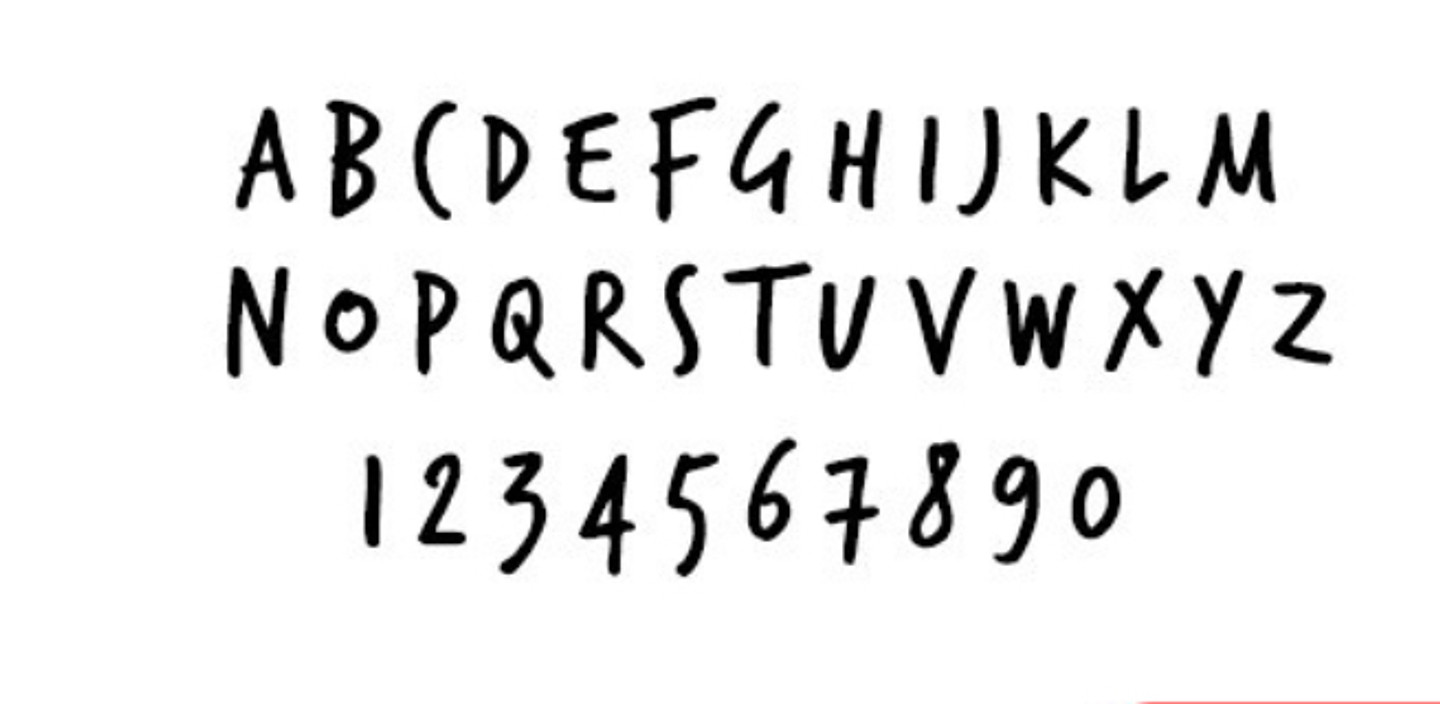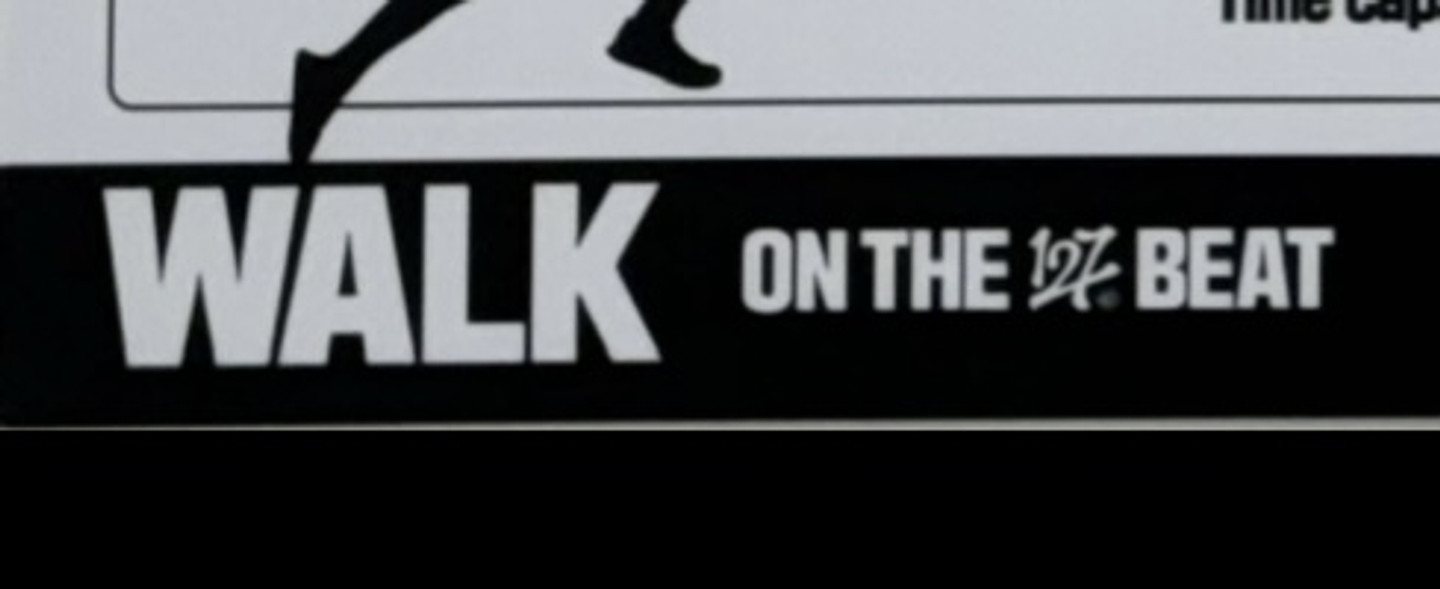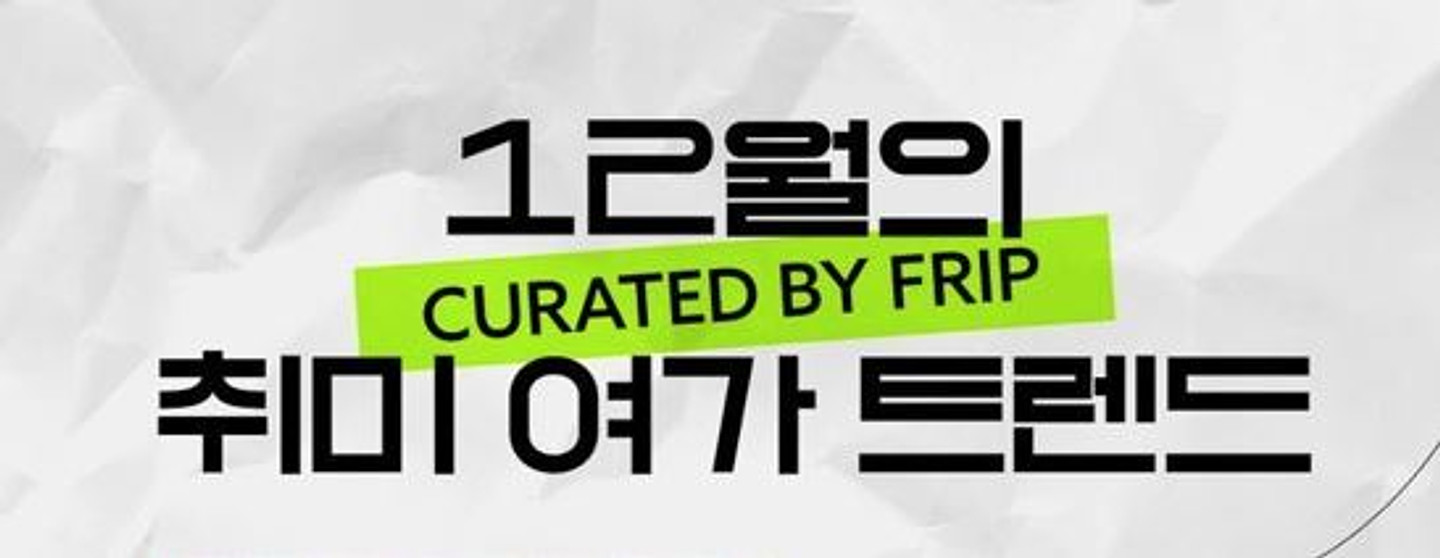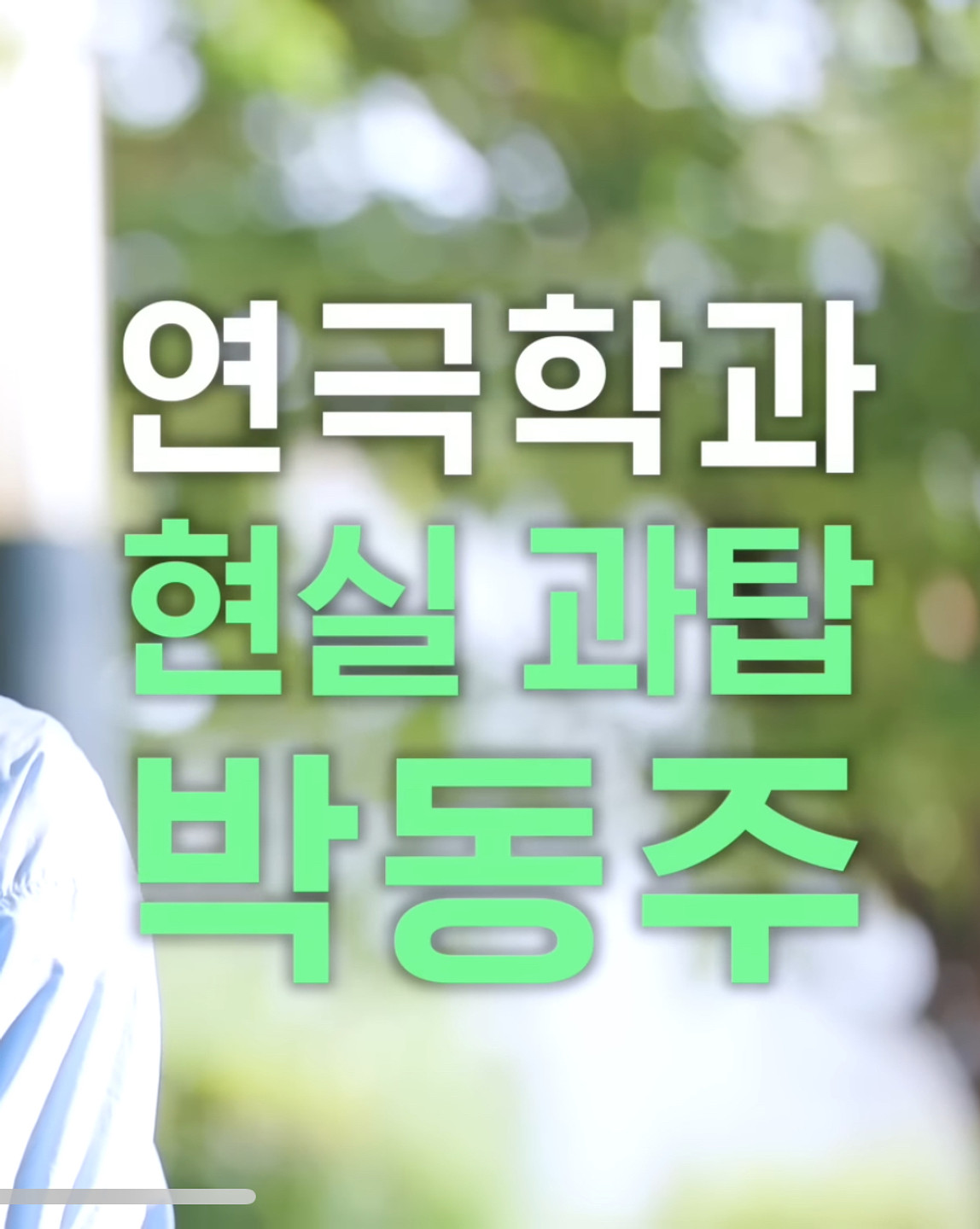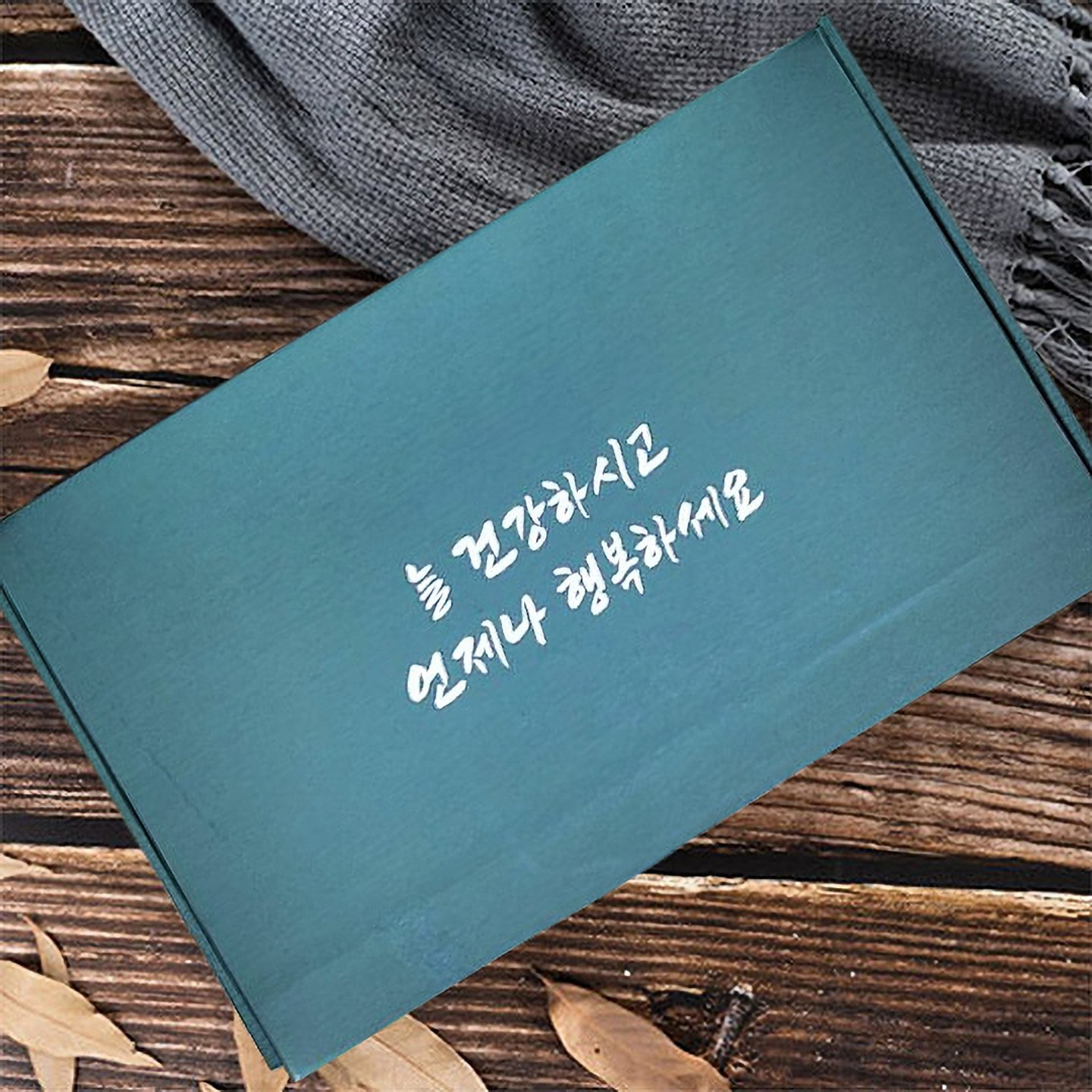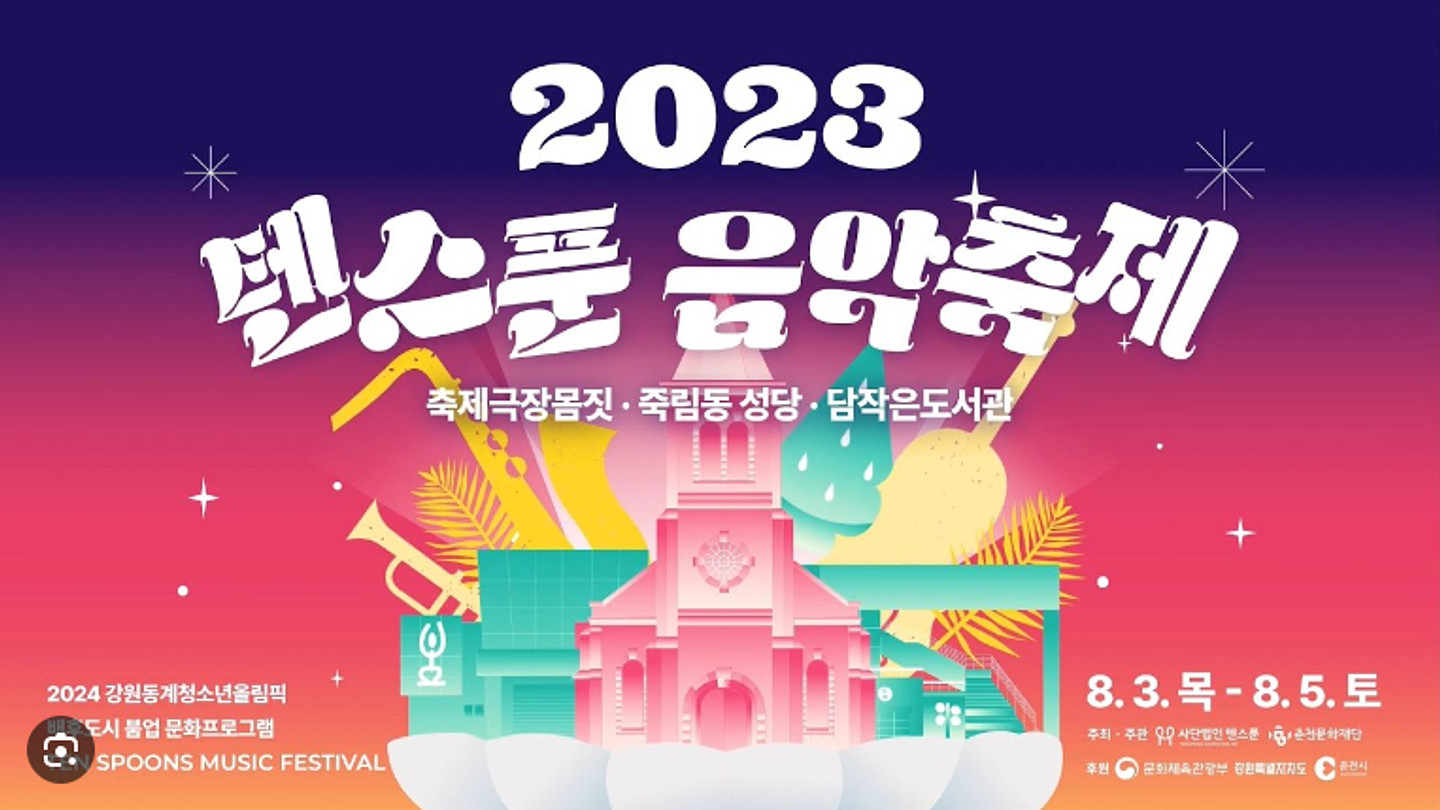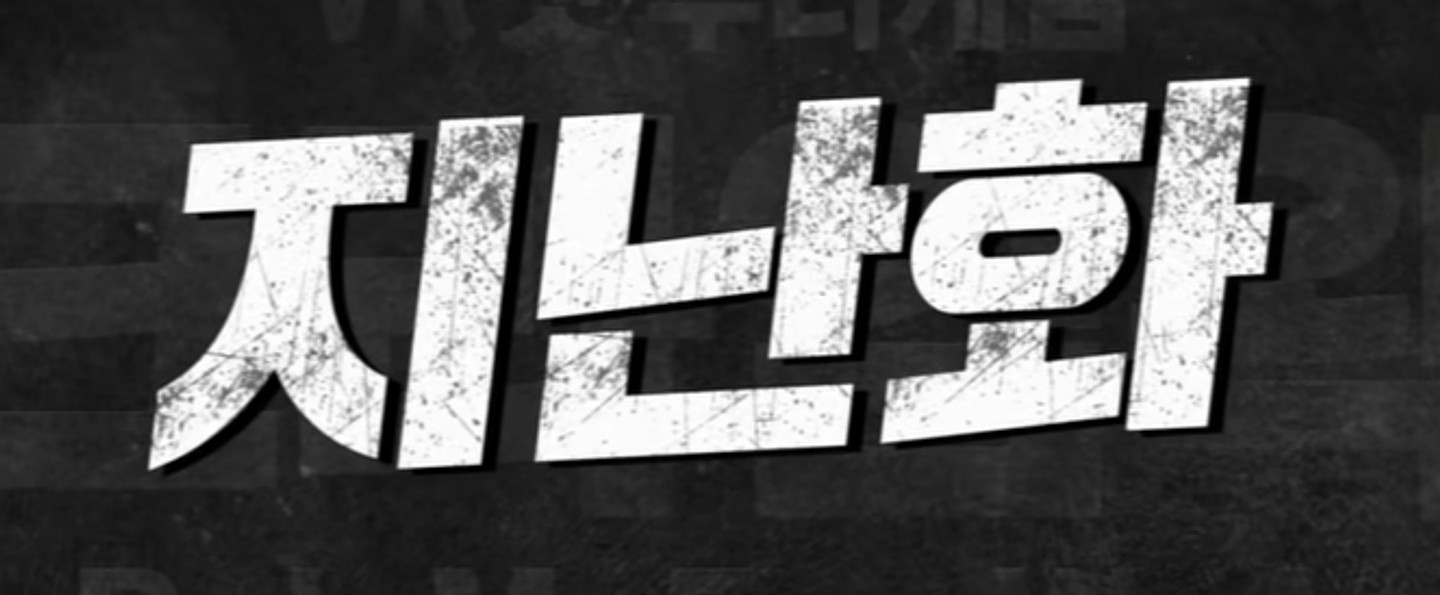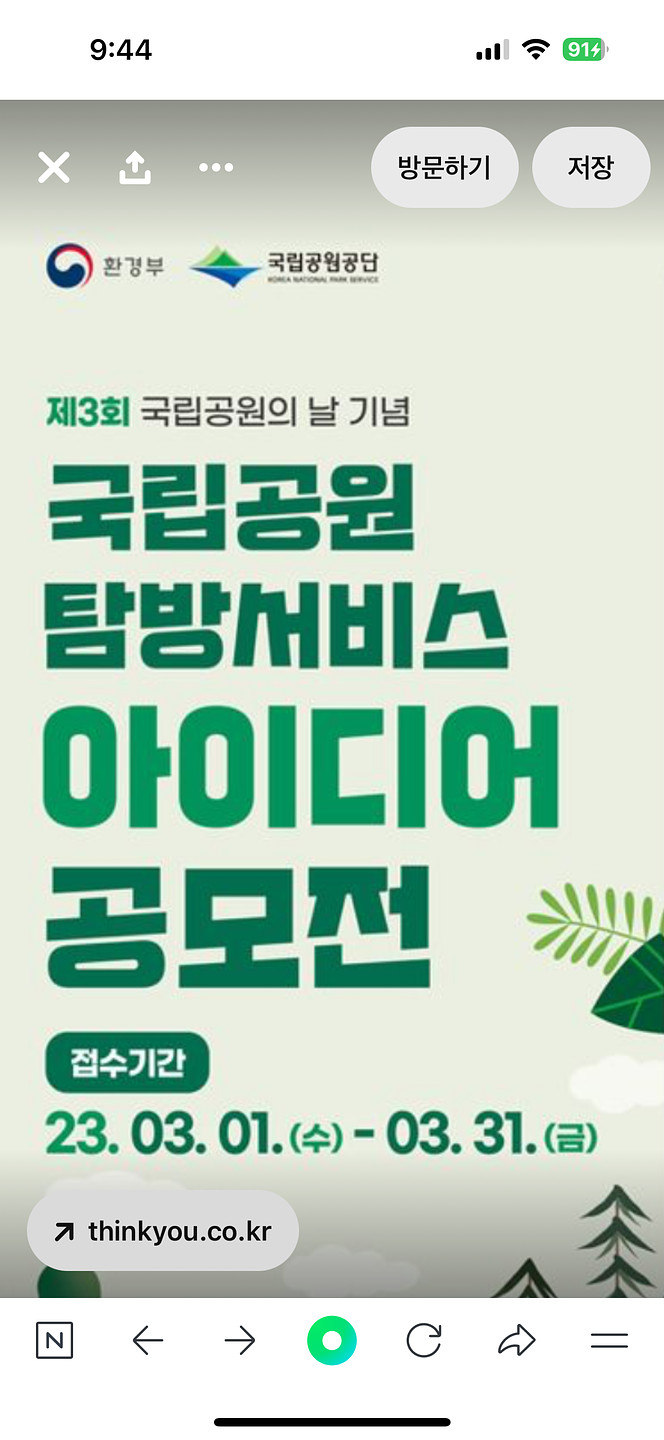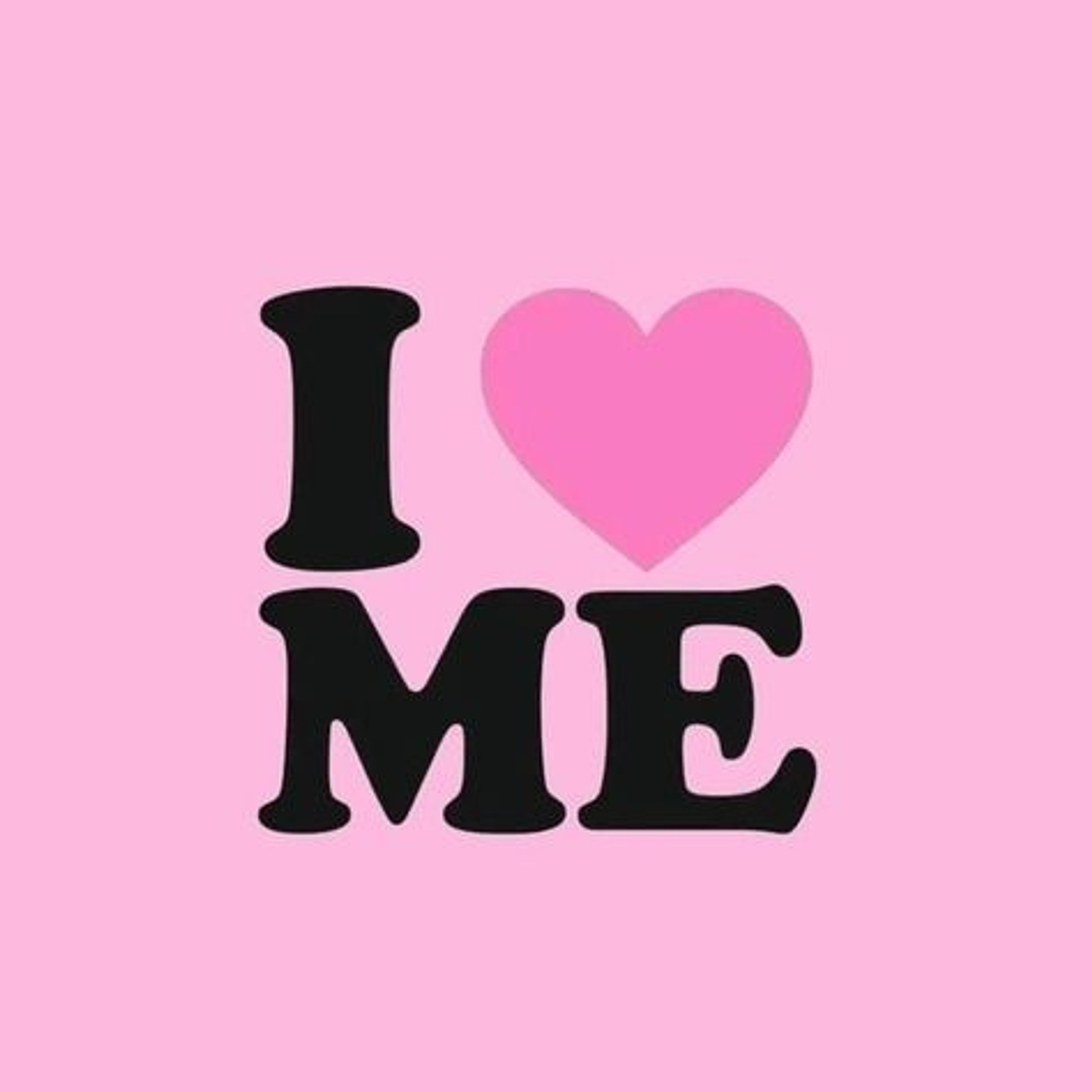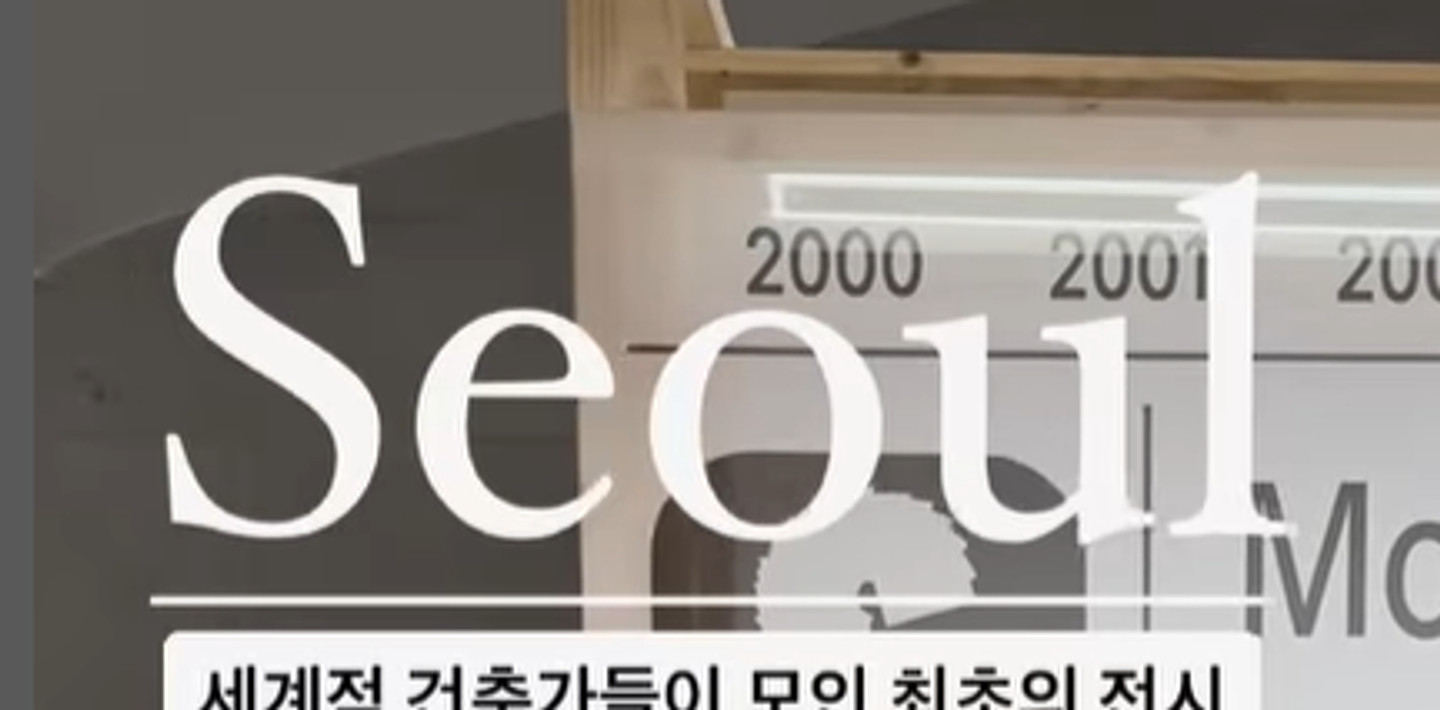
뭔폰트인가요
라라스윗 홈페이지 한글 폰트입니다!
찾아주세요
기아 타이거즈 기아 말고 타이거즈 부분만 ㅠㅠ 그리고 사진 하나밖에 못했는데 다른 구단들도 적어주세요
굵다
이거 무슨 폰트인가요...? 너무 궁금해요ㅠㅠ
여기 있는 두 폰트가 궁금해요🤔
케인님이 쓰시는 폰트인데 뭐인지 알려주실 수 있을까요..
범죄와의 전쟁 폰트 뭔지 아시는분 있으신가요? 아니면 비슷한 폰트라도 부탁드립니다
이거 무슨폰트인가요?JTBC News
ㅇ처럼 안에 포인트가 있는 서체인데 어떤 서체인가요?
수원fc 폰트가 무엇인가요
혹시 이 글씨체는 뭔지 알려주실 수 있나요??
이 폰트 뭔가요??
카라미 유튜브 갑충 이상형월드컵에 나온 첫 폰트입니다 궁금합니다
뭔가 특이한 폰트 이름 좀 알고 싶어요
귕여운건 항상 옳다 글씨체 궁금해요
채령) 이거 완전 이라고 적힌 글 폰트 궁금합니다ㅠㅠ
요 글씨체 궁굼해요..!
이 편성번호의 폰트를 알고싶어요!
이 영문폰트를 알고싶어요!
이 폰트 무엇인지 아시는 분 계실까요?
아마 노란 글씨랑 우측상단, 열차 내부 숫자랑 같은 폰트이고 서울교통공사 로고 제외한 다른 폰트들은 바탕 계열인 거 같은데 도저히 못 찾겠네요.
혹시 이 폰트 어떤건지 알려주실 수 있을까요..ㅠ
이거 궁금해요!! 미리 감사드립니다!!
이 폰트 좀 알려주세요
이 폰트 뭘까요? 그리고 저 반짝에서 이모티콘? 처럼 나오는거도 폰트의 일종인가요?? 프리미어에서 웽딩첸가 ㄱ그ㅓ랑 자체 이모티콘 써도 저 모양으로는 안나오더라구요ㅠㅠ
이 아이가 궁금합니다 ...
이거 폰트 이름 아시는 분 계시나요 ㅠ
캘리폰트같은데~ 정확한 폰트명을 모르겠어요~ 고수님들 부탁드립니다~^-6
폰트 이름 뭔지 아시는분계신가요?ㅜㅜ
No Problemo 영문 무슨 폰트인지 아시는 분 계실까요 ㅠㅠ 찾아주시면 정말 감사합니다… 운수대통하시길
캘리그라피인데 이거랑 유사한 폰트가 있을까요???
설렘 가득 집 꾸미기
이폰트 알수있을가요?
혹시 이 폰트 어떤 건가요?
제가 찾아본 것중에는 한나PRO체가 그나마 비슷한데 혹시 더 유사한 폰트 알고 있는 분 계실까요? 살려줍메!
무슨폰트 인지 아시는 분 계실까용?~~
무슨 폰트인지 아시는분 계실까요?!
이것도 무슨 폰트일지... 궁금하네요
무슨 폰트인지 아는 분 계실까요?
기본인듯 깔끔한데 어떤 폰트인가요
아무리 검색해도 안나오는데 무슨 폰트일까요 ㅠ?
법원 서류 보다가 봤는데 요 폰트 궁금해요
이 폰트 알고싶어요~!!
'서울염리초등학교' 글자는 무슨 폰트일까요?
이거 무슨폰트인가요..
이렇게 테두리 안에 공백으로 되어있는 폰트가 있을까요?
폰트 뭘까요??
예전에 폰트로 썼었는데 아웃라인 따서 찾을 수가 없네요 ㅠㅠ 영어폰트인데 찾아주시면 감사하겠습니다...ㅠ
안녕하세요 위 사진 무슨 폰트랑 가장 비슷할까요.. ?
넘 귀여워요 무슨 서체일까요?
이 폰트 무슨 폰트인지 아시는 분 계실까요?ㅠㅠ 바잇미 어플 로고입니다
리니지폰트 뭘까요?